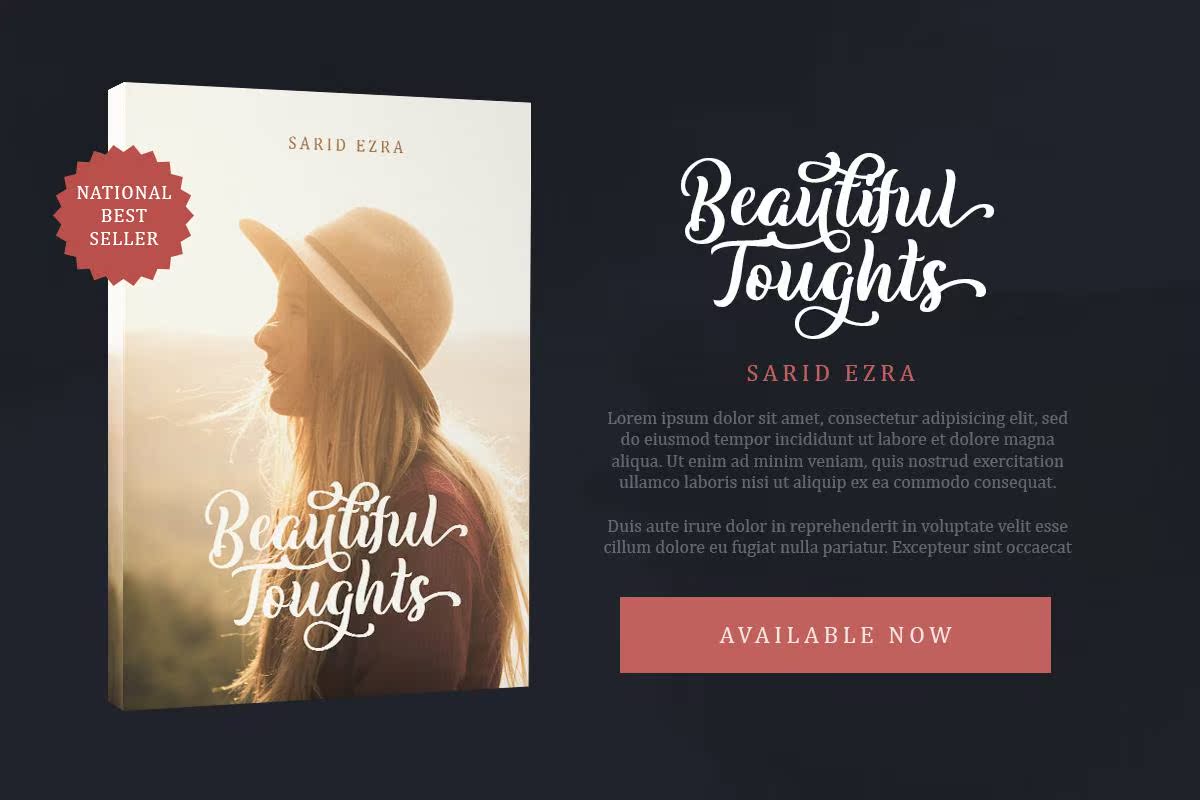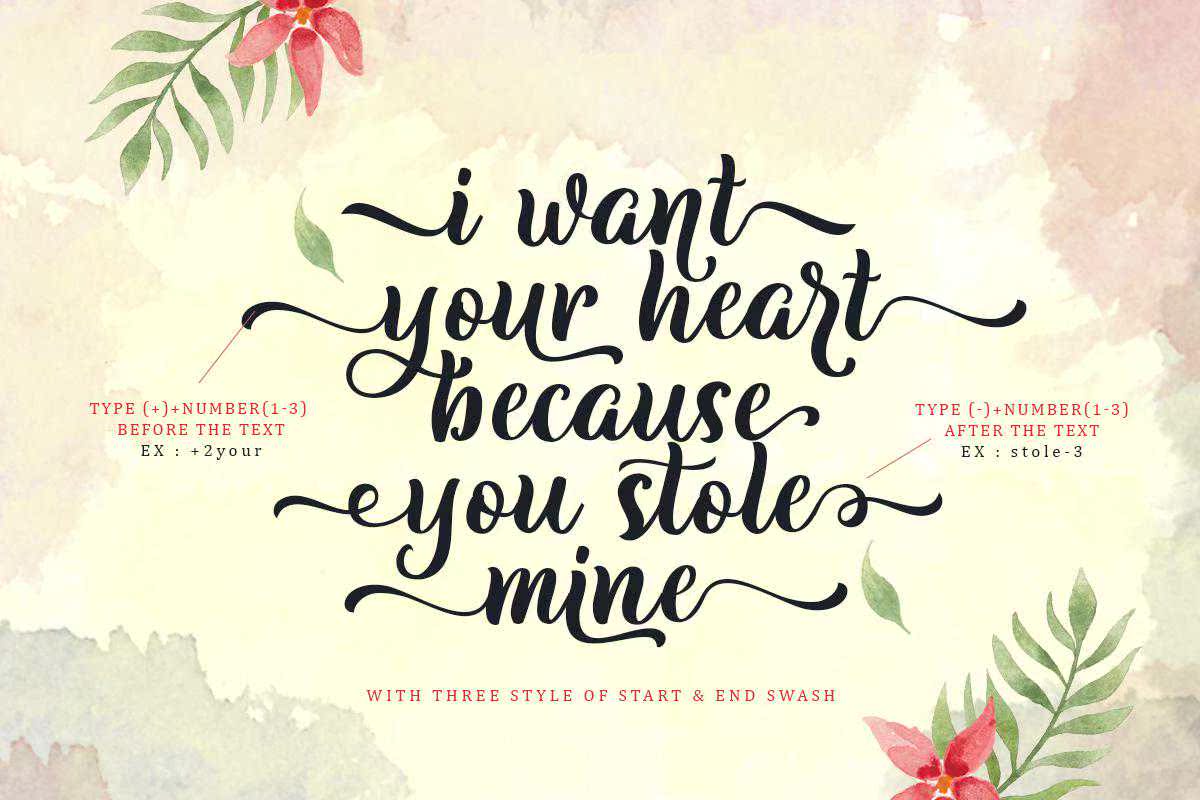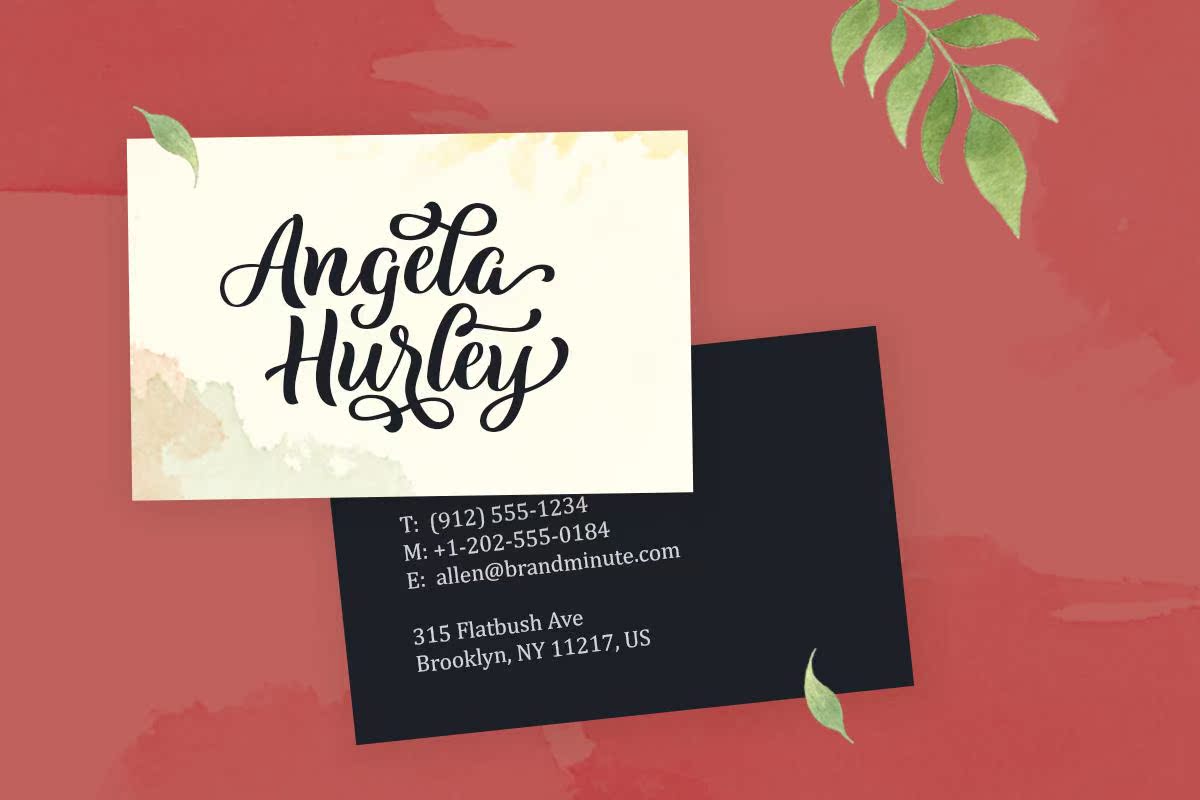
保加利亚,一个现代化的国家!自然手写脚本适用于标题、标识、服装、邀请函、品牌、包装、广告等需要使用字体的用户。该字体包括大写、小写、标点符号、符号和数字、样式设置替代、连字等,支持多语言。它也已经过UAN编码。保加利亚、Aromantic ModernScription Wistoff!自然手写脚本适用于标题、标识、服装、邀请函、品牌、包装、广告等需要字体的用户。该字体包括大写、小写、标点符号、符号和数字、样式设置替换、连字等,支持多语言。该字体也可以进行语音编码。